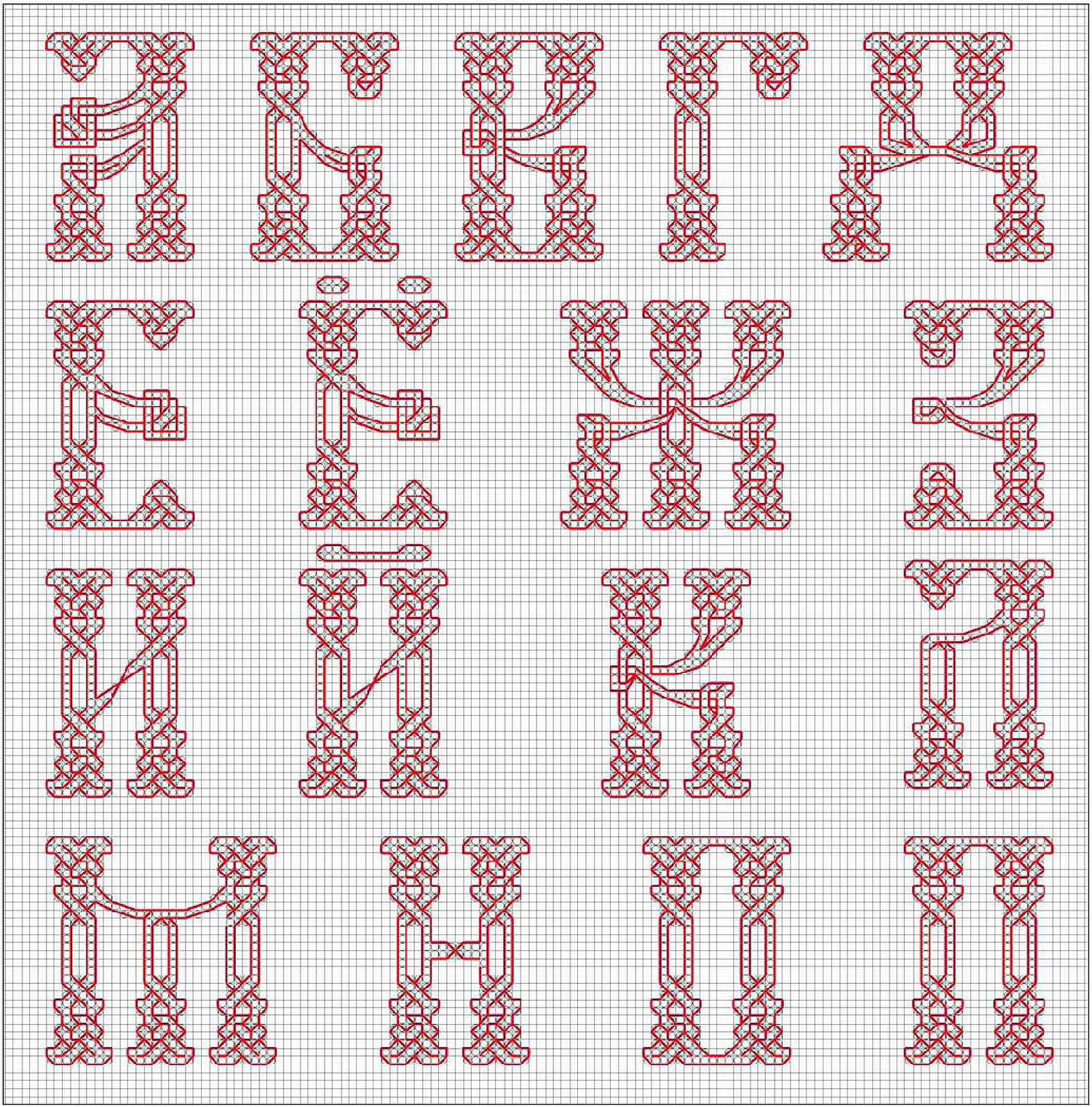
Босанчица – особая разновидность кириллического письма. Кириллица
КИРИЛЛИЦА
Древнейшие кириллические тексты
Древнейшие кириллические тексты, дошедшие до наших дней, – это надписи-граффити конца IХ–Х вв. на стенах и керамических плитах болгарских храмов и монастырей, на надгробиях болгарских царей и вельмож, предметах обихода и др.
К ним относится, прежде всего, т.н. преславская надпись, сделанная около 893 г., в самом начале правления царя Симеона (893–927) на стене Круглой церкви, также известной как Золотая или церковь св. Иоанна в бывшей столице Болгарии Преславе.
В надписи говорится, что церковь св. Иоанна построена хартофилаксом Павлом.
«цьркы сятааго иоана делае …
пауломь хартофулазомь»
По словам румынского слависта Д. П. Богдана, исследовавшего и издавшего в 1956 г. памятник, «Добруджанская надпись 943 г. – самая древняя кирилловская надпись, высеченная на камне и снабженная датой… С фонетической точки зрения Добруджанская надпись 943 г. приближается к древнеславянским текстам русской редакции (например, к Остромирову евангелию)».
Примерно к тому же времени относится кириллическая надпись на могильной плите болгарского сановника – «чергубыля» Мостича (около 960 г.). Она была обнаружена в Болгарии в Преславе в 1952 г. С. Ваклиновым. Датировать памятник помогает упоминание в ней болгарского царя Петра (927—969).«сьдележитъмо| стичьчрьгоубъɪ| лябъɪвъɪи при| сvмеонѣцр҃и| иприпетрѣцр҃и[о]с[м]иѭжедесѧ| тьлѣтъсъɪоста| вивъчрьгоубъɪлъ| ствоївьсеiмѣн| иѥбъɪстъчрьнори| зьцьiвътомьсъ| връшижизньсвоѭ».
«Здесь лежит Мостич чергубиля бывшый при царе Симеоне и при Петре царе. В восемдесят же лет сей оставив чергубильство и всё имение, был затем черноризец и в том (в иночестве) совершив жизнь свою».
Древнейшей из кириллических памятников с точно установленными датами считается т.н. Преспанская надпись или надпись царя Самуила 993 г.
В селе Айос Герман (до 1926 г. с. Герман), находящемся близ Преспы над озером Большая Преспа (на границе между Грецией и Македонией), найден надгробный камень с кириллической надписью, сделанной в 993 году по распоряжению царя Болгарии и Македонии Самуила на могиле его родственников. Она вырезана на углу плиты, стоявшей в усыпальнице Шишмановичей. Гробница, на которой был установлен камень, не найдена, но считается, что она находилась в церкви «Святой Герман» (сейчас Айос Германос), в которой до наших дней сохранились фрески, датируемые XI, XIII и XVIII вв. Деревня Айос Германос в настоящее время входит в состав муниципалитета Преспы (Греция).
«В името на отца и сина и светия дух. Аз, Самуил, поставям помен на баща си, майка си и братята си този кръст. Тези са имената на починалите: раб божий Никола, Рипсимия и Давид.
«Во имя Отца, Сына и Святого Духа, Я Самуил, раб Божий почитаю память отцу, мать и брату на этом кресте. Имена покоящихся здесь: Никола раб Божий, Рипсимия и Давид. Написал в году 6501 от Сотворения мира (=993г.)».
Камень хранится в Национальном историческом музее Болгарии в Софии. Его копия находится в с. Самуилова-Крепость, Благоевградская область, (Болгария).
Древнейшие хорватские кириллические тексты
Первые обнаруженные кириллические записи в Хорватии относятся к XII в. и известны как «Povaljski prag» и «Povaljska listina».
На о. Брач в г. Повля, во время реставрации бенедиктинского монастыря была открыта кириллическая надпись 1184 г. т. н. «Povaljski prag» («Повальский архитрав»). Она вырезана на архитраве дверного проема в середине западной монастырской стены (длина 124 см, средняя ширина 22 см.). Этот повальский памятник культуры – древнейший памятник хорватской кириллической письменности, одна из самых красивых и самых старых среди сохранившихся хорватских кириллических надписей.
«Ja, majstor Radonja,sazidao sam ova vrata radi Gospodina Boga, i da imam dijela u ovoj crkvi».
«Я, мастер Радонья, построил сам эту дверь ради Господа Бога, и у меня есть участие в этой церкви».
В тексте упоминается имя первого хорватского знаменитого каменщика мастера Радоньи.
Оригинал «Повальского архитрава» хранится в Музее хорватских археологических памятников в Сплите.
Над порталом была обнаружена также копия описи имущества аббатства 1184 г., сделанная 1 декабря 1250 г. сплитским священником Иоанном – т. н. «Povaljska listina» («Повальская грамота»).Эта Повальская грамота представляет собой известный литературный и исторический памятник и является одним из старейших хорватских языковых, культурных и церковно-юридических документов.
В настоящее время «Povaljska listina» хранится в приходском архиве села Пучишча здесь же на о. Брач.
Красивый шрифт онлайн, написать им текст онлайн
Не знаете как написать красиво текст? Тогда вы попали по адресу
Владельцы многих сайтов стараются написать красиво текст, который публикуется на страницах их ресурса, и тому есть весьма веские причины.
Как известно, 80% информации человек воспринимает через зрительные каналы связи, но при этом простой текст плохо усваивается по сравнению с обычным изображением.
1. Сервис Online Letters
Один из самых известных сайтов подобной тематики в рунете это http://online-letters.ru/ .
— Мы начинаем с четырех замечательных, продуманных дизайнов, работать с которыми в качестве установленных шрифтов было очень приятно. Мне нравятся точечные детали в Codarte.